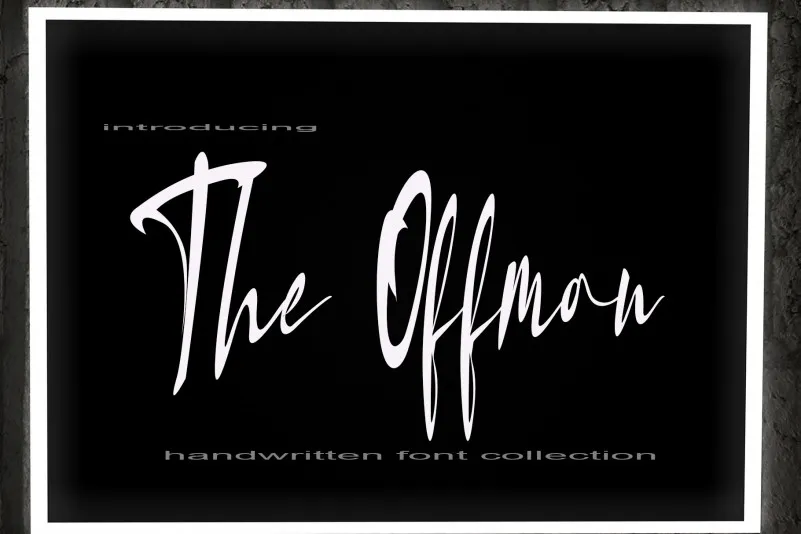
A fonte “The Offman Font” é uma elegante tipografia cursiva que traz consigo um toque único e impactante. Seus traços delicados e naturais enriquecem qualquer projeto de design, conferindo a ele um brilho luxuoso. Como parte do catálogo de fontes escrita à mão da kateengciu, “The Offman Font” é perfeita para criar designs que expressam sofisticação e personalidade. Composta para quem valoriza a autenticidade no design gráfico, esta fonte será um marco imprescindível em sua coleção de recursos digitais. Engane-se se pensar que apenas projetos profissionais podem beneficiar desta fonte: ela enriquece trabalhos pessoais e artesanais com uma graça única, tornando o processo de criação mais gratificante do que nunca.